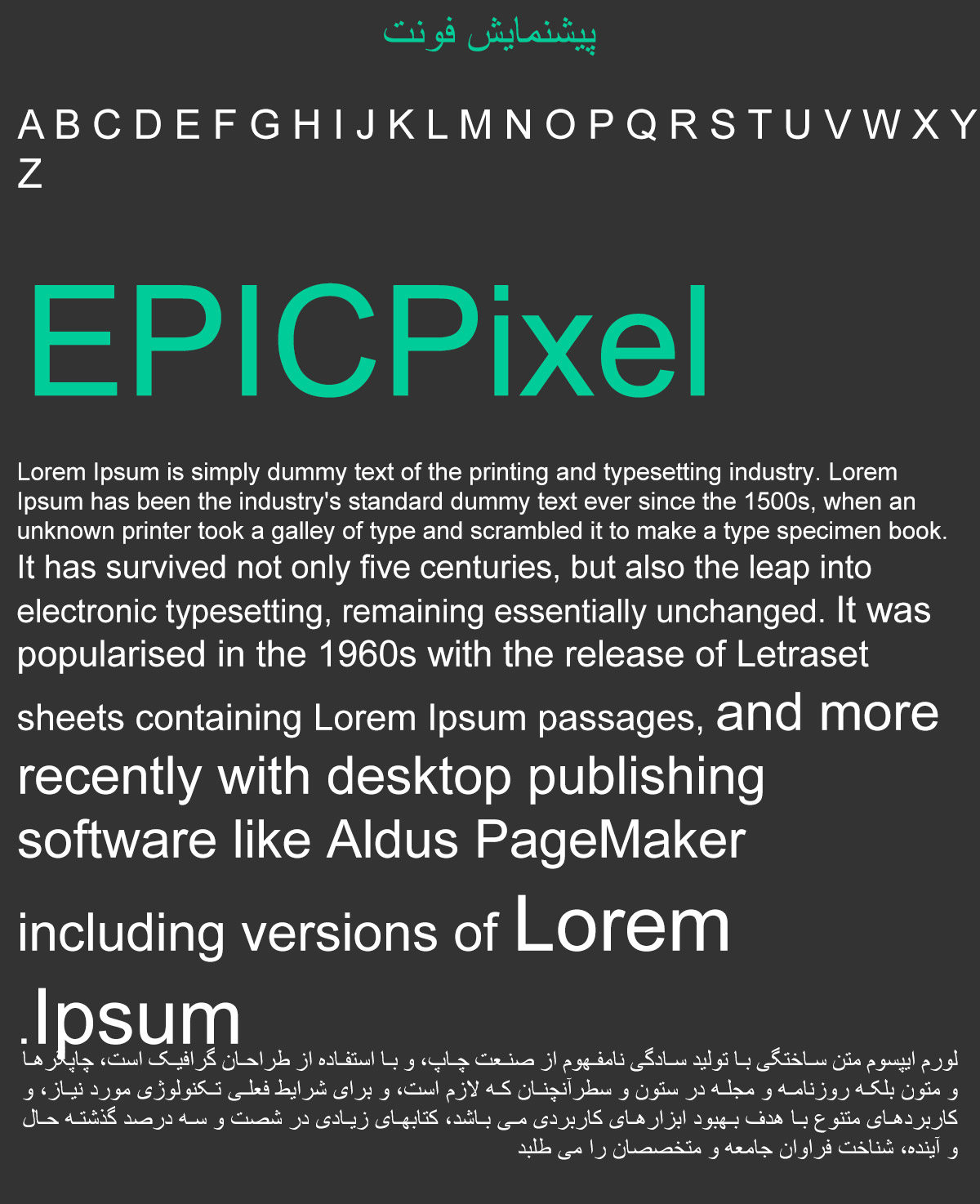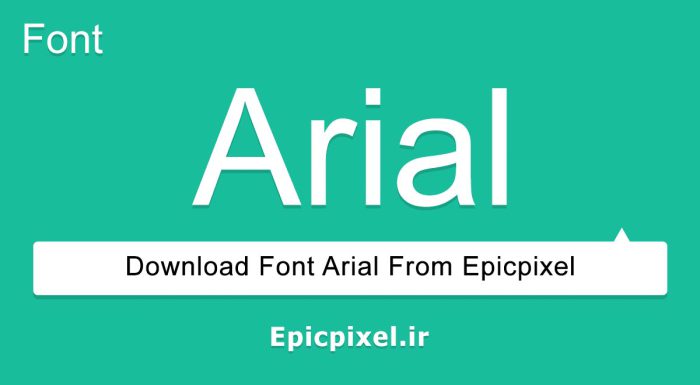
فونت Arial یک تایپ فیس سان سریف (sans-serif) در سبک نئو-گروتسک است که در سال ۱۹۸۲ توسط رابین نیکلاس و پاتریشیا ساندرز برای شرکت Monotype طراحی شد. این فونت با هدف ارائه جایگزینی برای Helvetica و بهینه سازی برای پرینترهای لیزری با رزولوشن پایین، توسعه یافت. Arial به دلیل خوانایی بالا، ظاهر خنثی و صنعتی، و تطبیق پذیری فوق العاده، به یکی از پرکاربردترین فونت ها در سراسر جهان تبدیل شده است. این فونت به طور گسترده در تمامی نسخه های مایکروسافت ویندوز (از ویندوز ۳.۱ به بعد)، macOS اپل و بسیاری از پرینترهای PostScript 3 قرار گرفته است. Arial برای استفاده شخصی رایگان است و نسخه های متنوعی از جمله Arial Black، Arial Narrow، Arial Rounded MT Bold و Arial Unicode MS را شامل می شود.
فونت Arial به عنوان یکی از رایج ترین و شناخته شده ترین تایپ فیس ها در جهان، حضوری گسترده در محیط های دیجیتال و چاپی دارد. این فونت در سال ۱۹۸۲ توسط رابین نیکلاس و پاتریشیا ساندرز در شرکت Monotype طراحی شد. هدف اصلی از طراحی Arial، ایجاد یک تایپ فیس سان سریف برای پرینترهای لیزری با رزولوشن پایین IBM بود، به همین دلیل در ابتدا با نام Sonoran Sans Serif عرضه شد.
تاریخچه و توزیع:
- در سال ۱۹۹۲، مایکروسافت Arial را به عنوان یکی از چهار فونت اصلی TrueType در ویندوز ۳.۱ انتخاب کرد و آن را به عنوان “جایگزینی برای Helvetica” معرفی نمود. این تصمیم نقش مهمی در گسترش وسیع Arial داشت.
- Arial Unicode MS، نسخه ای از Arial با پشتیبانی از کاراکترهای گسترده یونیکد، از سال ۱۹۹۹ تا ۲۰۱۶ همراه با مایکروسافت آفیس عرضه می شد.
- Arial همچنین در macOS اپل و بسیاری از دستگاه های PostScript 3 پشتیبانی می شود.
ویژگی های طراحی:
- ظاهر خنثی و صنعتی: Arial دارای ظاهری ساده، بدون زرق و برق و صنعتی است که خوانایی بالایی را فراهم می کند.
- پایه های مورب (Diagonally Cut Terminals): یکی از ویژگی های متمایزکننده Arial، پایانه های مورب در برخی از ضربه ها (مانند حروف c، e، g، s) است که به آن ظاهری کمتر مکانیکی می بخشد.
- ویژگی های انسانی تر: در مقایسه با بسیاری از فونت های سان سریف قبل از خود، Arial دارای ویژگی های انسانی تری است که منحنی های نرم تر و پرتر را در خود جای داده است.
- تطابق با Helvetica: Arial به گونه ای طراحی شده که از نظر معیارها (Metric Compatible) با Helvetica همخوانی داشته باشد، به این معنی که اسناد می توانند بدون تغییر در چیدمان بصری، از هر یک از این دو فونت استفاده کنند. اگرچه باور رایج این است که Arial بر اساس Helvetica طراحی شده، اما دقیق تر است که Monotype Grotesque را جد آن بدانیم، با تأثیراتی از Helvetica و Venus.
خانواده فونت و نسخه ها: خانواده فونت Arial بسیار گسترده و شامل انواع زیر است:
- Arial Italic: نسخه مورب.
- Arial Bold: نسخه پررنگ.
- Arial Bold Italic: نسخه پررنگ مورب.
- Arial Black: وزنی بسیار سنگین.
- Arial Narrow: نسخه فشرده (برای جای دادن متن بیشتر در ستون های باریک).
- Arial Rounded MT Bold: نسخه با گوشه های گرد.
- Arial Unicode MS: نسخه با پشتیبانی گسترده از کاراکترهای یونیکد.
- Arial Light, Arial Medium, Arial Extra Bold, Arial Condensed: نسخه های دیگر که توسط Linotype عرضه شده اند.
- Arial Alternative: نسخه های خاصی که ظاهر مونواسپیس برای سیستم های تلکست را شبیه سازی می کنند.
- Arial Nova: نسخه ای جدیدتر بر اساس فونت های بیت مپ Sonoran Sans از سال ۱۹۸۲، که از ویندوز ۱۰ به بعد عرضه می شود.
مجوز و جایگزین های رایگان: Arial یک تایپ فیس اختصاصی (Proprietary) است و شرکت Monotype Imaging تمام حقوق آن را در اختیار دارد. با این حال، برای استفاده شخصی رایگان است و به طور گسترده در سیستم عامل ها توزیع می شود. برخی جایگزین های رایگان و هم تراز (Metrically Compatible) برای Arial وجود دارند، از جمله:
- Liberation Sans: توسعه یافته توسط Ascender Corp. و منتشر شده توسط Red Hat.
- Nimbus Sans L: توسط URW++ تولید و تحت مجوز GPL منتشر شد.
- FreeSans: از پروژه ی GNU FreeFont.
- TeX Gyre Heros: توسط گروه کاربران TeX لهستان (GUST).
کاربردهای فونت Arial در طراحی و اسناد
فونت Arial به دلیل سادگی، خوانایی بالا و حضور گسترده، در طیف وسیعی از کاربردها در اسناد، وبسایت ها، و مواد تبلیغاتی مورد استفاده قرار می گیرد.
کاربردهای اصلی:
- اسناد شرکتی: به دلیل ظاهر تمیز و حرفه ای، Arial گزینه ای رایج برای گزارش ها، ارائه ها (پاورپوینت)، و مکاتبات اداری است.
- طراحی وب: این فونت برای نمایش بر روی صفحات نمایش بهینه شده است و خوانایی واضحی را در انواع دستگاه ها تضمین می کند.
- تبلیغات و چاپ: Arial با ظاهر واضح و صیقلی خود، برای بروشورها، فلایرها و پوسترها مناسب است.
- متون عمومی: به عنوان یک فونت خنثی، به خوبی در انواع متون عادی و عمومی به کار می رود و خوانایی بالایی را به ارمغان می آورد.